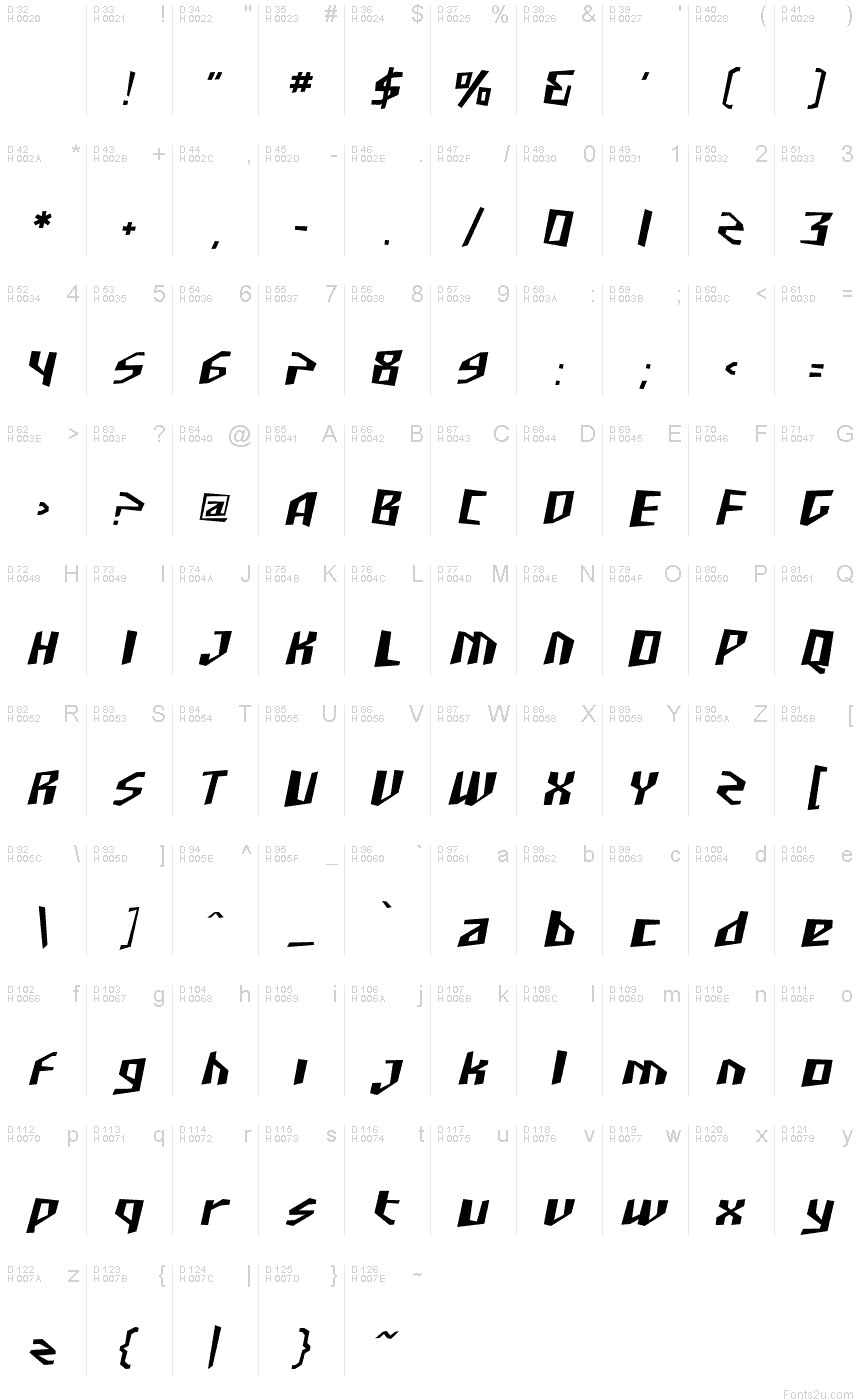
SF Junk Culture Oblique od ShyFoundry to bezpłatny krój pisma typu display w stylu punk, z poszarpanymi, ręcznie wycinanymi wielkimi literami i niespokojnym, przechylonym rytmem. Litery wyglądają jak wycięte z zinów i ulotek klubowych – masywne czarne kształty o ostrych kątach, z nierównymi łączeniami i surowym, improwizowanym charakterem, który nadaje alfabetowi napięcia i wyrazistości.
Ten darmowy font idealnie pasuje do ulotek muzycznych, grafik deskorolkowych, okładek płyt, marki streetwearowych i zbuntowanych opakowań, gdzie zbyt czysty styl wydawałby się zbyt ułożony. Użyj go do krótkich nagłówków, tekstów na okładki, plansz tytułowych czy monogramów, gdy chcesz, aby wielkie litery wyglądały jak sklejone z kawałków, a nie starannie narysowane.
Prezentacja i próbka wizualna czcionki SF Junk Culture Oblique
SF Junk Culture
Oblique
ShyFoundry
Derek Vogelpohl